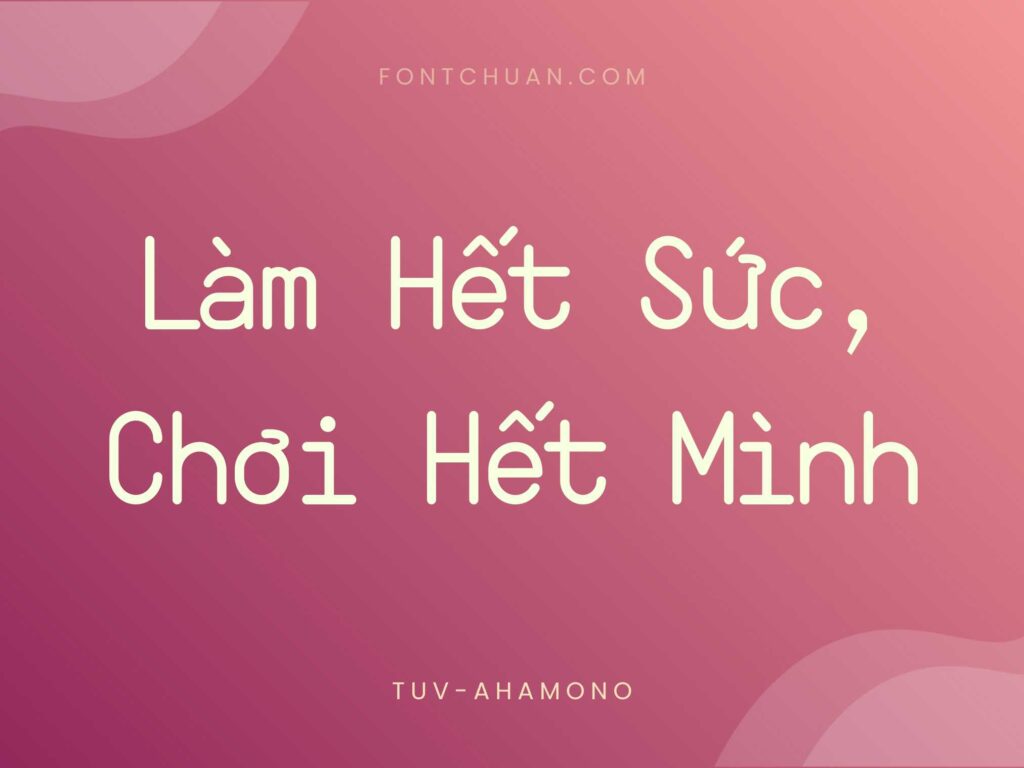
Font TUV Ahamono Việt Hóa
Tác giả Font: Alfredo Marco Pradil
Việt hóa bởi: Thùy Uyên
Ahamono là một Font Monospace với thiết kế bo tròn, được tạo ra bởi Alfredo Marco Pradil và phát hành bởi Hanken Design Co. Font này có các ký tự với chiều rộng cố định, phù hợp cho việc sử dụng trên web và giao diện người dùng (UI). Với thiết kế chữ in hoa và in thường, Ahamono giúp hiển thị nhiều chữ trên một không gian hẹp, đặc biệt hiệu quả khi sử dụng làm tiêu đề. Font đã được Việt hóa để hỗ trợ tiếng Việt bởi Thùy Uyên, giúp người dùng Việt Nam dễ dàng áp dụng trong các dự án thiết kế. Font này được sưu tầm và chia sẻ bởi thành viên của Font Chuẩn, đáp ứng nhu cầu sử dụng đa dạng trong cộng đồng thiết kế.
Đặc điểm thiết kế của Ahamono bao gồm các nét chữ bo tròn và chiều rộng cố định, tạo cảm giác hiện đại và gọn gàng. Font này phù hợp cho các ứng dụng như thiết kế tiêu đề, logo, giao diện người dùng và các dự án sáng tạo khác. Các ngành nghề phù hợp bao gồm công nghệ, quảng cáo và giáo dục.